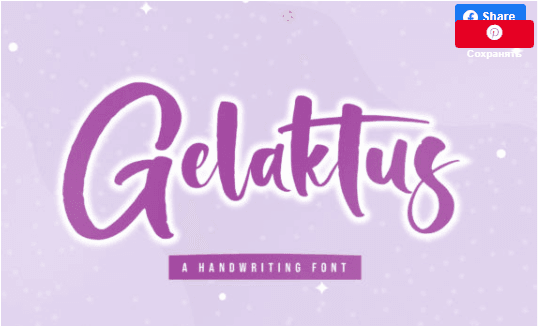
Gelaktus Font
Gelaktus — изящный и плавный рукописный шрифт. Он также закодирован PUA, что означает, что вы можете легко получить доступ ко всем глифам и росчеркам! Этот шрифт определяется естественным потоком и непринужденной атмосферой, и в результате он будет соответствовать широкому спектру творений.